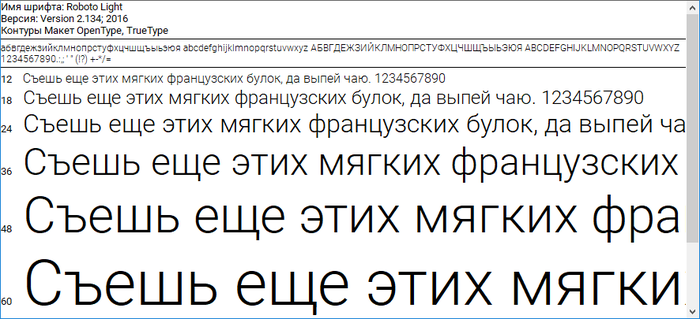
Как заменить системный шрифт UI Windows
Тем не менее, мне хотелось бы затронуть тему изменения пользовательского интерфейса (UI) на комплукторах по аналогии с гайдлайнами от гугл или эпл. Что такое гайдлайны можно почитать на примере “google material” для android, лучше сразу на английском языке. Что бы разнообразить интерфейс на своём смартфоне достаточно сменить обои. А вот с со своим ноутом или компом на винде всё чуточку сложнее. Помимо обоев мы всегда и везде взаимодействуем с текстом. В случае windows 10 (все редакции) шрифт Segoe UI смотрится не плохо, но если взять за основу “единство визуальной составляющей”, то начинает иметь смысл идея заменить шрифт в самой ОС.
Мне, как андроид юзеру, захотелось найти нужный шрифт и заменить им системный винды.
Тот самый шрифт, который без рута (для любителей курсива есть отдельный котёл) распространён в андроиде, начиная с 4й версии называется Roboto. Да же сейчас, если ты сидишь через приложение Pikabu видишь этот шрифт.
Из Wiki:
Roboto (робото) — шрифтовая гарнитура без засечек, представленная вместе с операционной системой Android 4.0 «Ice Cream Sandwich». Google описывает шрифт как «современный, но доступный» и «волнующий».
Шрифт Roboto содержит все символы RU и EN раскладок.